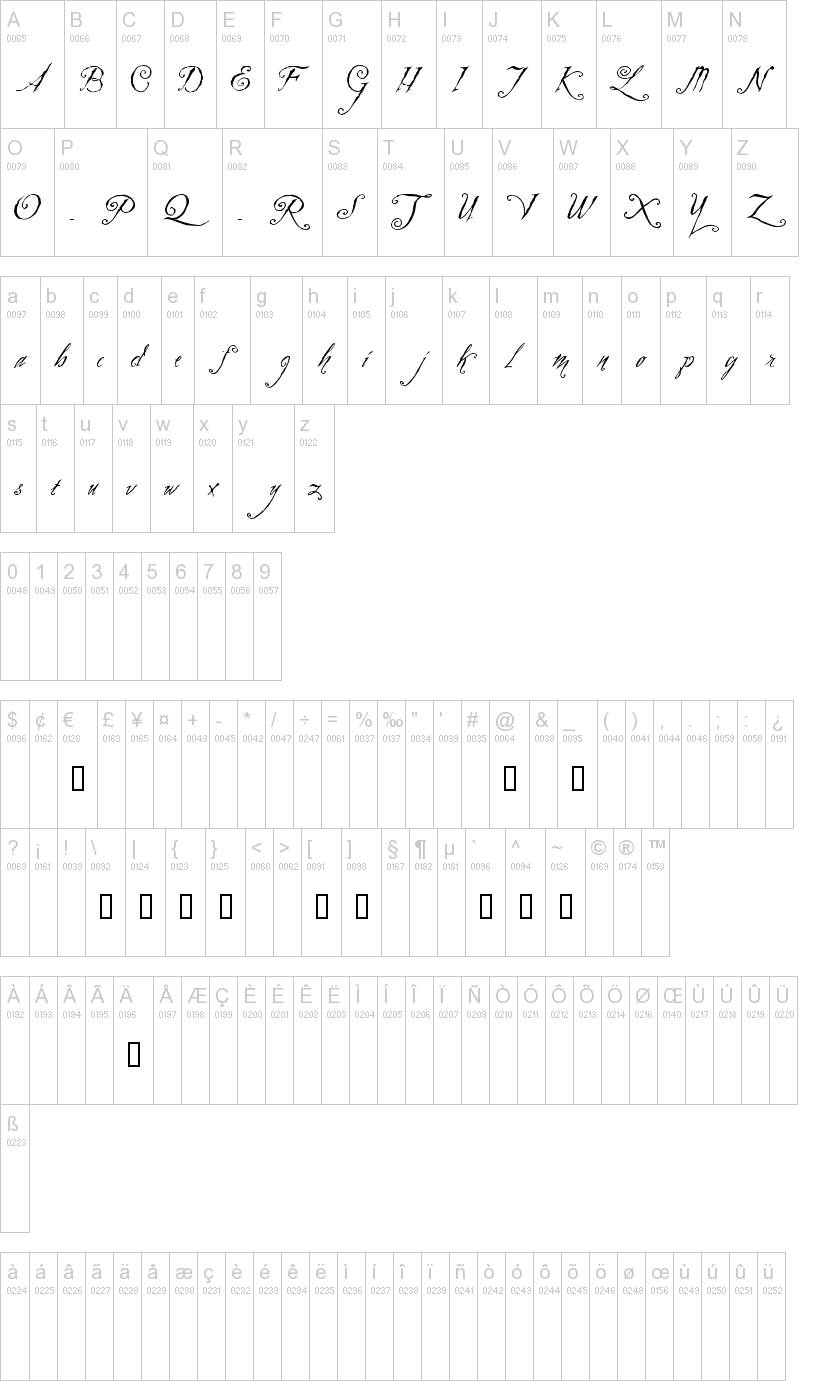
Zothique是一种装饰性的字体,由设计师Juanjo López创建。它的灵感来自于H.P. Lovecraft所创造的虚构世界“Zothique”,这是一个黑暗、神秘、邪恶的地方。因此,这种字体的设计也是以此为灵感,富有神秘感和古老感,适用于一些冒险、幻想、奇幻类的设计项目或素材。 Zothique字体的特点是具有高度的装饰性和独特的笔画。它的字母形状非常奇特,有些字母的笔画甚至超出了字母的轮廓,营造出一种神秘而独特的氛围。 此外,Zothique字体也提供了一些连字符、下划线和其他符号,可以用来强调某些文字,让它们更突出。因此,如果您需要设计一些富有冒险、神秘感和古老感的素材或项目,Zothique字体将是一个不错的选择。内容介绍
Zothique是一款非常不错的手写艺术字体,具有很好的视觉感,适合于文化类的宣传设计、商业类品牌的广告和产品包装设计以及个性化文字排版等较多场景。